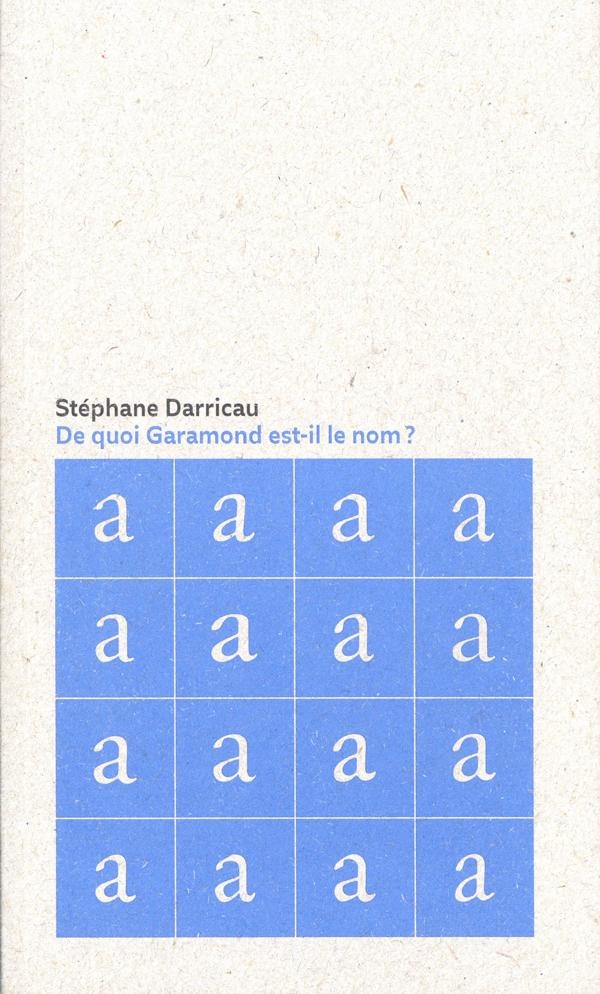
DE QUOI GARAMOND EST-IL LE NOM ?
De quoi Garamond est-il le nom ? S'attachant à décrire et à expliciter l'histoire du plus célèbre des caractères typographiques classiques et de ses multiples avatars modernes et contemporains, cet ouvrage participe tout autant de la culture historique de la typographie que des enjeux de sa pratique contemporaine. A travers l'exemple du Garamond, ce sont les relations que les designers, les éditeurs et les lecteurs entretiennent avec le médium typographique qui se trouvent analysées et mises en perspective.